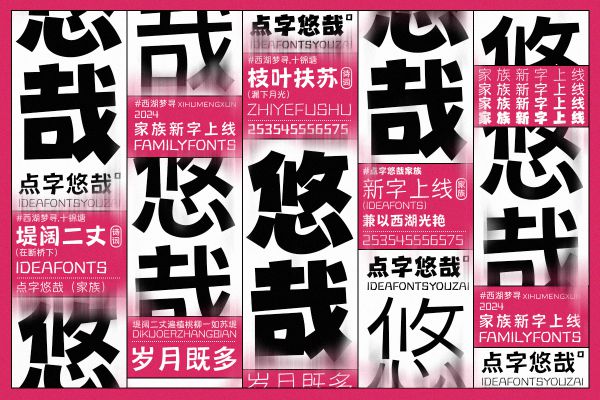
点字悠哉 25
点字悠哉 95 是点字库推出的创意黑体字体,以“复古趣味+超粗字重”为核心亮点,融合黑体的稳重与创意设计的灵动,成为会员商用场景中的个性之选。 字体字形方正大气,重心居中平衡,中宫设计适中,既保留黑体的扎实结构,又通过细节巧思打破沉闷:笔型融入斜切处理与装饰元素,方头笔画利落如刀削,笔画连接处的“断开”设计暗藏巧思——横画收笔的斜切角度、竖画末端的迷你装饰,让每个字符都带着复古俏皮的节奏感。超粗字重赋予字体浑厚饱满的体量感,而笔画间若隐若现的轻微弧度与右上倾斜态势,又让方正结构透出婉转韵律,恰似“悠然自得”的生活态度具象化,尽显“俏皮不失端庄”的独特气质。 作为适配商业设计的实用字体,点字悠哉 95 兼顾视觉冲击力与场景适配性:复古海报标题中,超粗字重强化吸睛效果;潮玩包装或文创LOGO里,趣味装饰元素传递轻松氛围。无论是追求复古风潮的品牌塑造,还是需要趣味表达的创意项目,这款字体都能以“稳而不板,趣而不俗”的设计语言,为文字注入鲜活生命力,让商业设计兼具个性与亲和力。